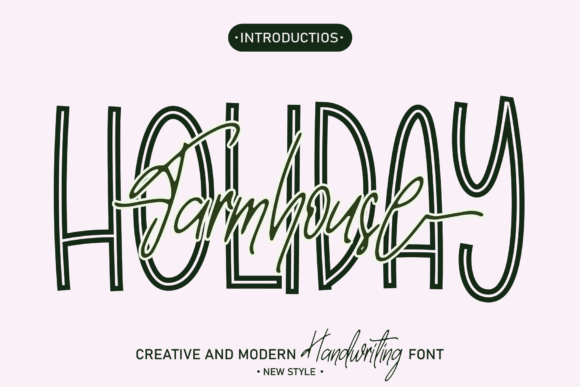
Farmhouse Holiday
適切なデザイン要素を見つけるのは難しい場合がありますが、Farmhouse Holidayは作品を即座に引き立てる優れたコレクションを提供します。
POD(オンデマンド印刷)製品、結婚式の招待状、またはソーシャルメディアのグラフィックを作成している場合でも、Farmhouse Holidayは理想的です。